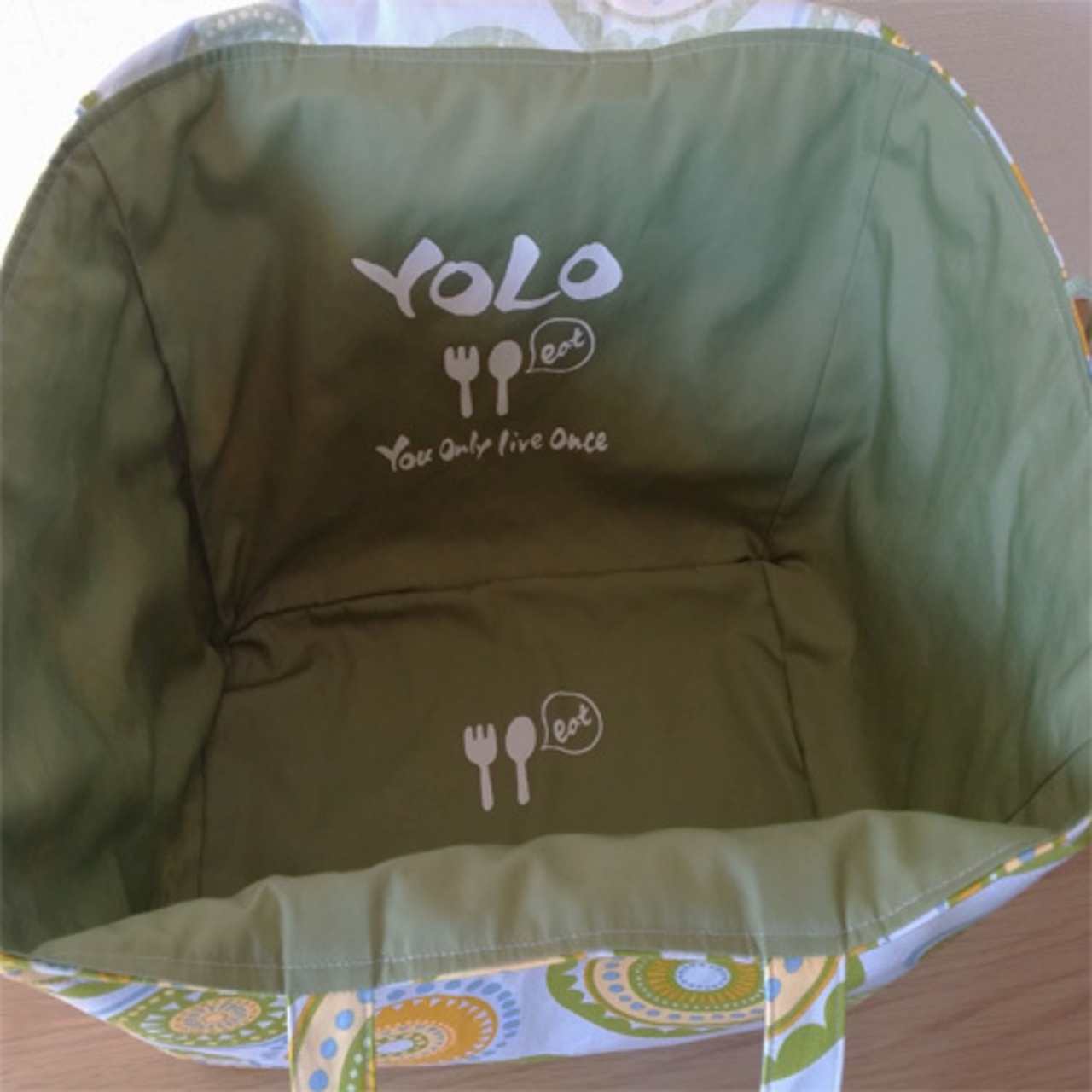
レジかごバック☆エキゾチック&オリエンタルLast
エキゾチックなオリエンタル柄・・・これで最後です。
最後はビタミンカラーで登場です( *´艸`)フフッ
パステルグリーン&パステルブルーな色合いがこれから訪れる暖かい季節にピッタリ!
裏地には「YOLO」をバッチリ印刷していきましたよ~♪
スーパーの買い物だけじゃなく、夏のお出掛けやレジャーにも物をザクザク入れて持って行って下さい♡
肩に掛けて持ち歩けるように持ち手は60cm&軽量☆☆☆
汚れたって大丈夫!布製ですからお洗濯OK♪いつも清潔に保てます。
ゆるりが筆で書いた文字やイラストを裏地または表地にシルクスクリーン印刷で仕上げたオリジナルの生地をどちらかに使っています。
使い方は超簡単
お買い物精算時にレジかごにバックをセットすれば、詰め替える手間も省けキレイに入れてもらえてとっても便利!!(写真参考)
サイドに紐が付いているので大量の買い物でも横から物が落ちにくくなってます。
蓋付きだから、中身も見えにくい!
更に更に!使わないときはたたんでおいて置けるベルト付き♡